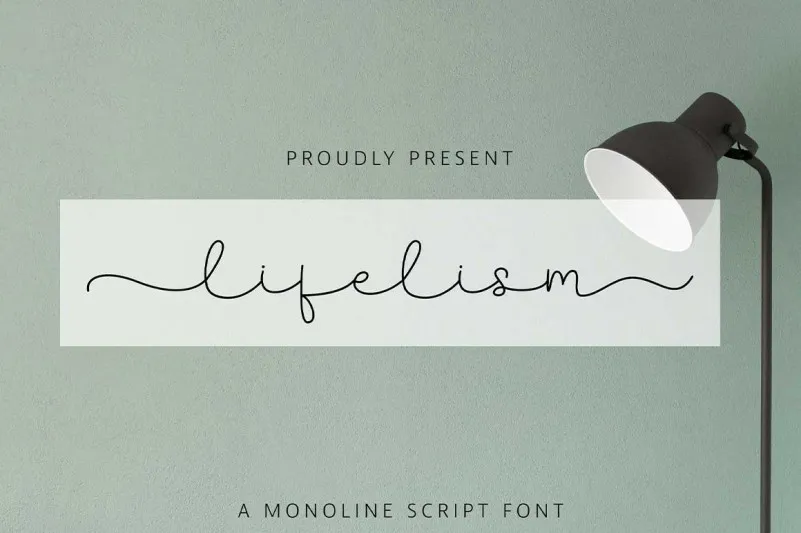
Lifelism Font – Fonte Grátis
Lifelism Font
A Lifelism Font é uma tipografia script monolínea criada pelo JunCreative com um estilo de assinatura escrita à mão. Ela oferece caracteres elegantes e bem equilibrados, o que a torna perfeita para projetos variados. Se você está sempre buscando novas ideias criativas ou desenhando trabalhos impecáveis, esta fonte é definitivamente para você. Adicione-a aos seus projetos mais imaginativos e observe como ela os torna ainda mais vivos! Esta elegante tipografia combina facilmente com uma ampla variedade de designs, tornando-a perfeita tanto para iniciantes quanto para profissionais de design.